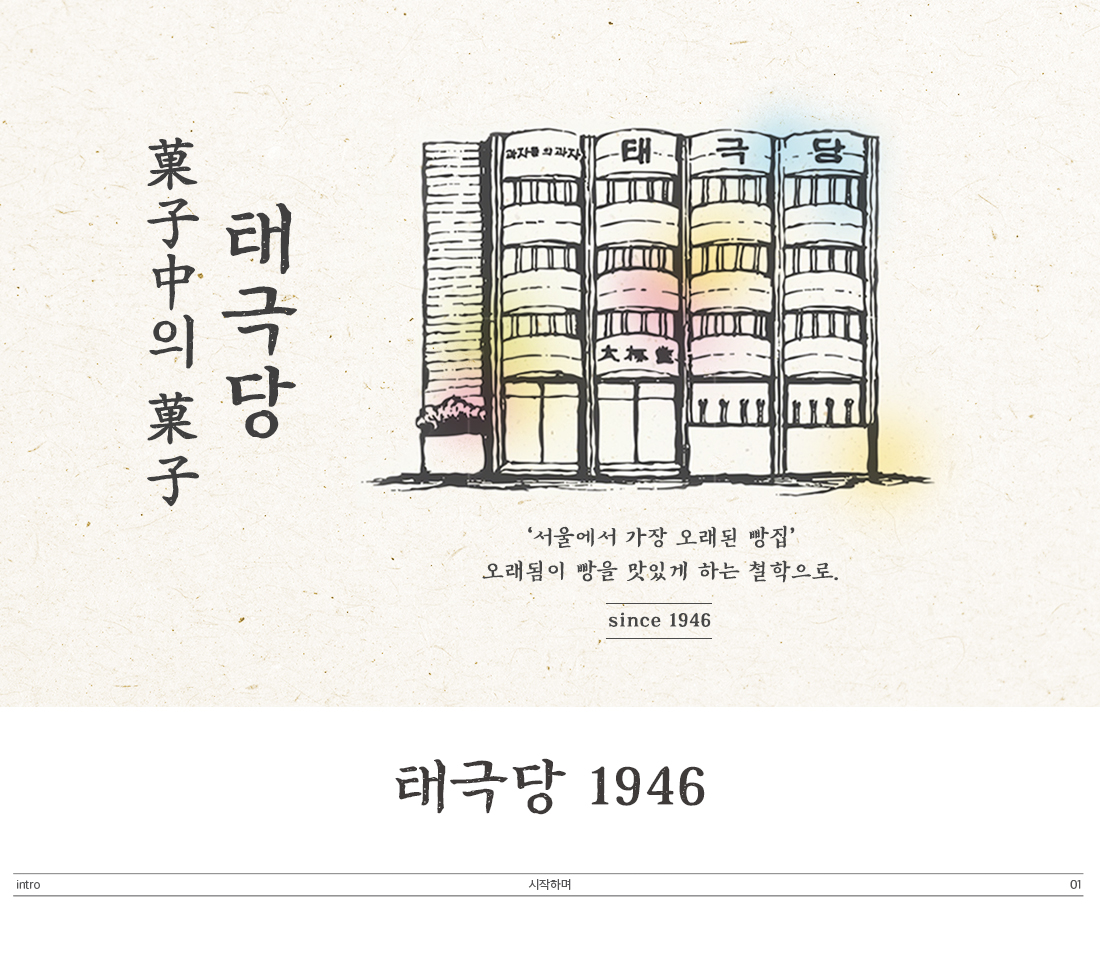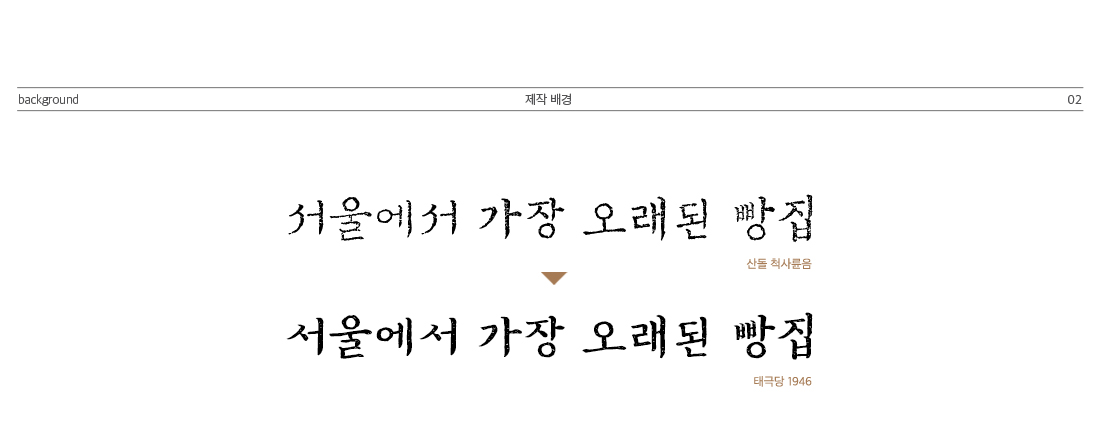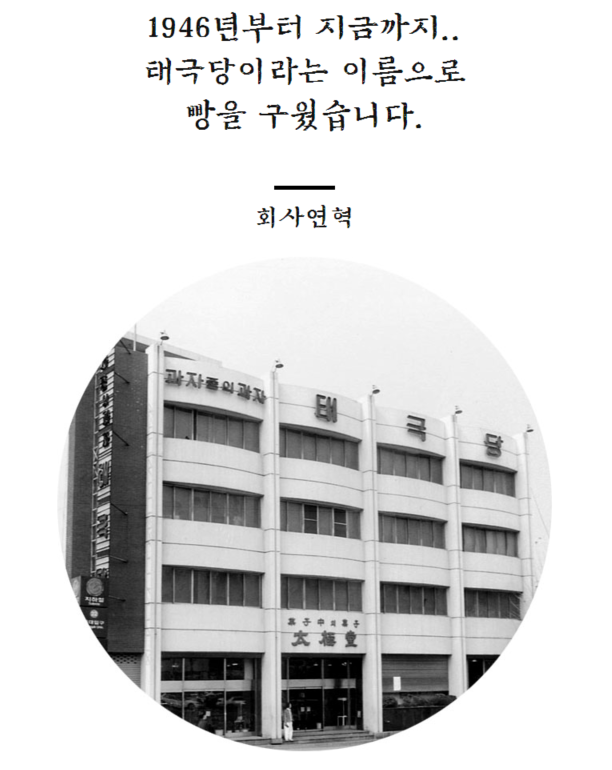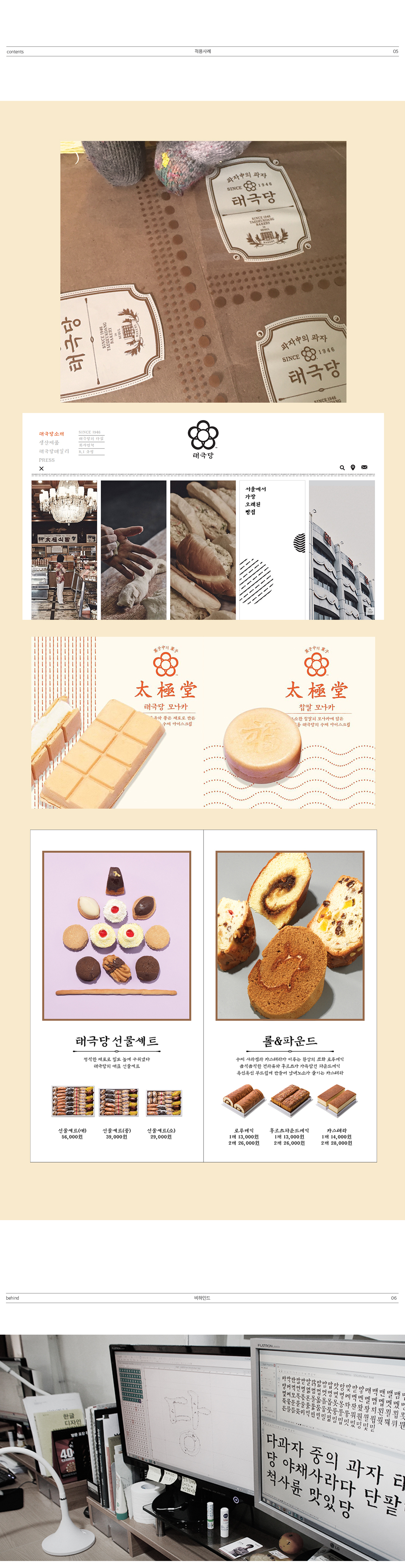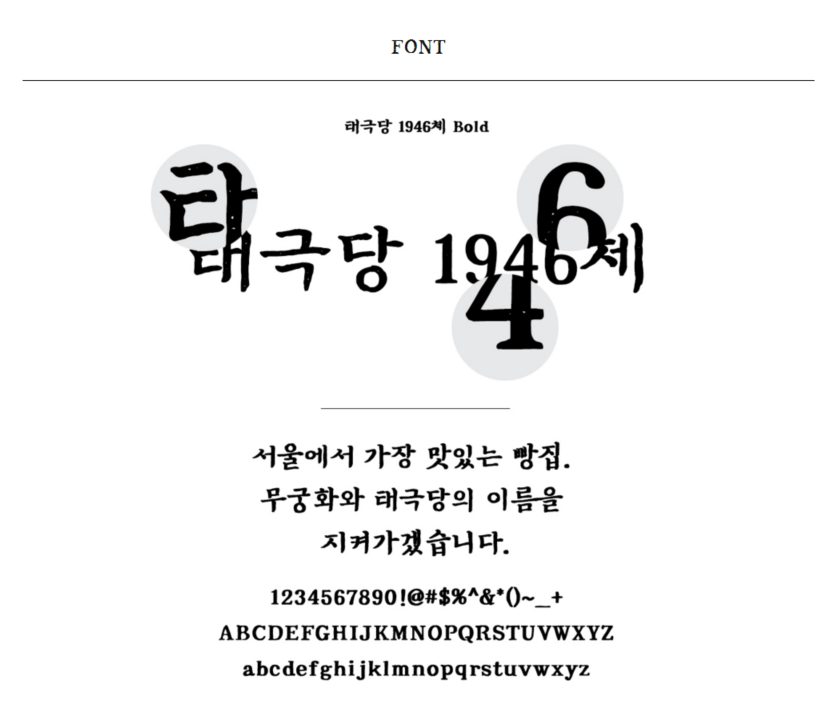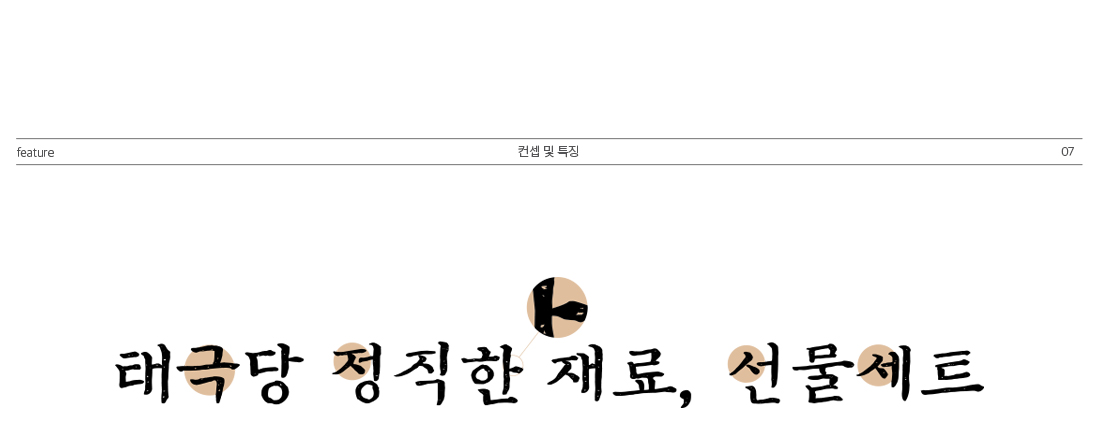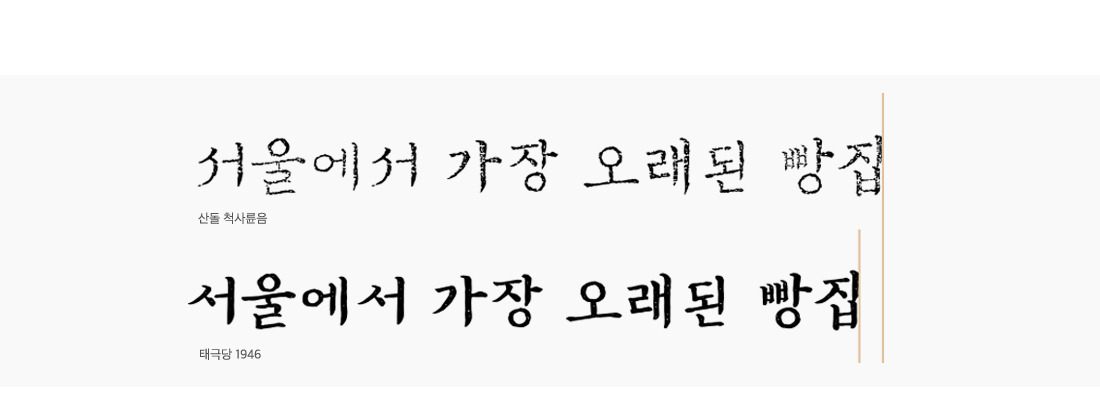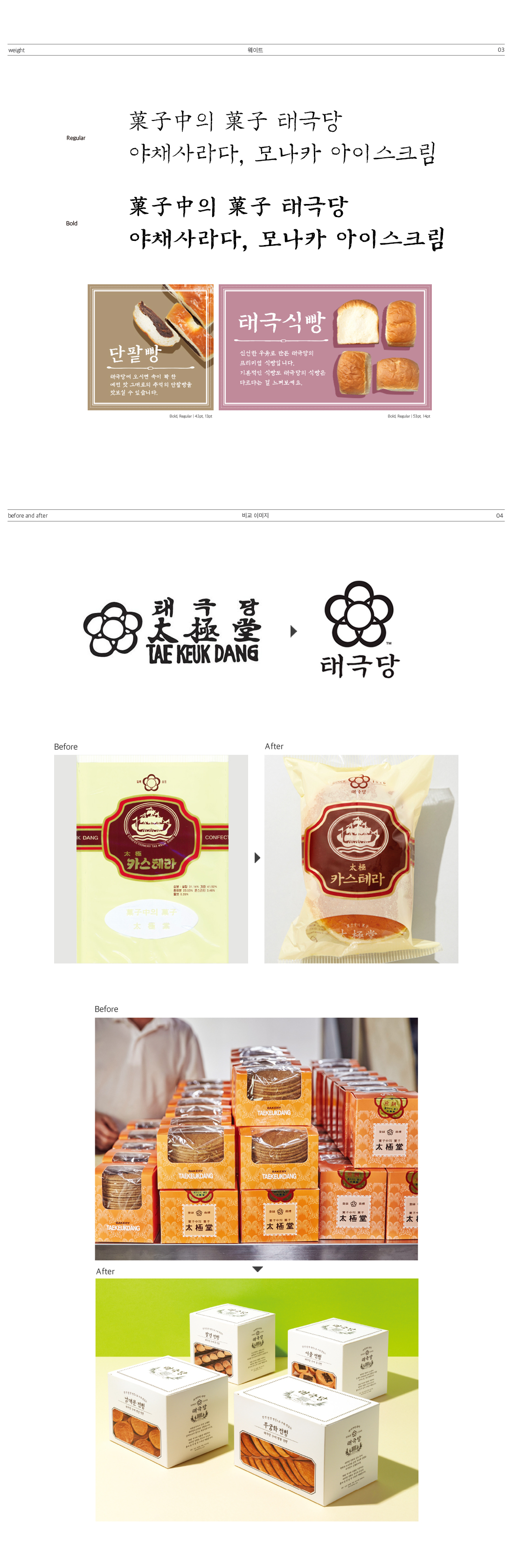
타이포브랜딩 : 한땀 한땀 공들인, 태극당 전용서체
서울에서 가장 오래된 빵집을 아는가? 바로 장충동에 있는 태극당이다. 빵을 위해 목장을 세웠다는 일화에서 알 수 있듯이 맛있는 빵에 대한 철학을 그대로 이어온 태극당에서 그들만의 전용서체를 제작하게 되었다.
타이포브랜딩 : 태극당 전용서체
서울에서 가장 오래된 빵집을 아는가? 바로 장충동에 있는 태극당이다. 광복 직후, 광복의 때를 기다린 듯 태극당이란 이름을 내건 빵집이 서울에 문을 열었다. 그로부터 70년이 훌쩍 지난 지금도 3대를 이어 그 세월의 맛을 이어오고 있는 곳. 빵을 위해 목장을 세웠다는 일화에서 알 수 있듯이 맛있는 빵에 대한 철학을 그대로 이어온 태극당에서 그들만의 전용서체를 제작하게 되었다.
제작배경
이러한 태극당의 전통과 맛에 대한 철학에 잘 어울리는 전용서체를 만드는 것이 이 프로젝트에서 가장 중요했다. 산돌이 보유한 폰트 중에 ‘척사륜음’이 세월의 흔적과 함께 멋스러움까지 느껴져서 이것을 커스터마이징해서 새롭게 제작했는데, 만들고보니 태극당과 잘 어울리는 선택이지 않았나 싶다.
1946년, 무려 70년 전에 ‘태극당’이 설립되었다. (출처-태극당 홈페이지)
컨셉 및 특징
# 글자가 커지면 커질수록 나타나는 적절한 질감 표현과, 곁줄기가 안쪽으로 들어오는 ㅓ, ㅔ 계열의 초성 ㅅ, ㅈ, ㅊ 의 형태를 태극당에 맞게 수정됨
# 전체적인 밸런스 조정으로 두께나 크기 등이 척사륜음에 비해 고르게 수정되었고, 글자 사이의 간격을 알맞게 조정하여 글줄 길이가 적절하게 줄어듦
웨이트
적용사례
시작부터 끝까지 어려웠다. 아니, 어렵다기보다는 고된 작업이었다. 기존 ‘척사륜음’ 폰트는 오래된 글자의 느낌을 내기 위한 질감 표현이 강했다. 글자를 확대해보면 자잘한 파편들이 떨어져 나간 것처럼 보이는데, 새로운 태극당 전용서체는 이것들을 하나하나 합치고 이어주는 단순 반복작업의 연속이었다.
시간을 단축해보려 필터나 레벨값 조정 등의 기능을 활용해 보았지만 척사륜음의 정갈하고 깔끔한 느낌이 사라지고 뭉개지는 경우가 많았다. 결국, 한땀 한땀 정공법으로 글자를 만들어 나가야 하는 과정이었고 그 결과로 태극당 1946 폰트가 탄생하였다.
이렇게 한땀 한땀 공들여 탄생한, 태극당 1946
국문 폰트명 : 태극당 1946
영문 폰트명 : Taegeukdang 1946
제작 구분 : 커스터마이징
웨이트 : 2종
글자 구성 : 한글 2,350자 / 영문 94자 / KS약물 986자 / 한자 20자
출시년도 : 2014년